15 font chữ viết tay vintage
Nếu bạn đang tìm kiếm những font chữ mang phong cách cổ điển và sang trọng để làm mới thiết kế của mình, thì đừng bỏ qua bài viết này. Những font chữ viết tay vintage sẽ không chỉ làm nổi bật vẻ đẹp cổ điển, mà còn mang đến sự hấp dẫn và độc đáo cho bất kỳ dự án nào.
Font chữ viết tay là gì?
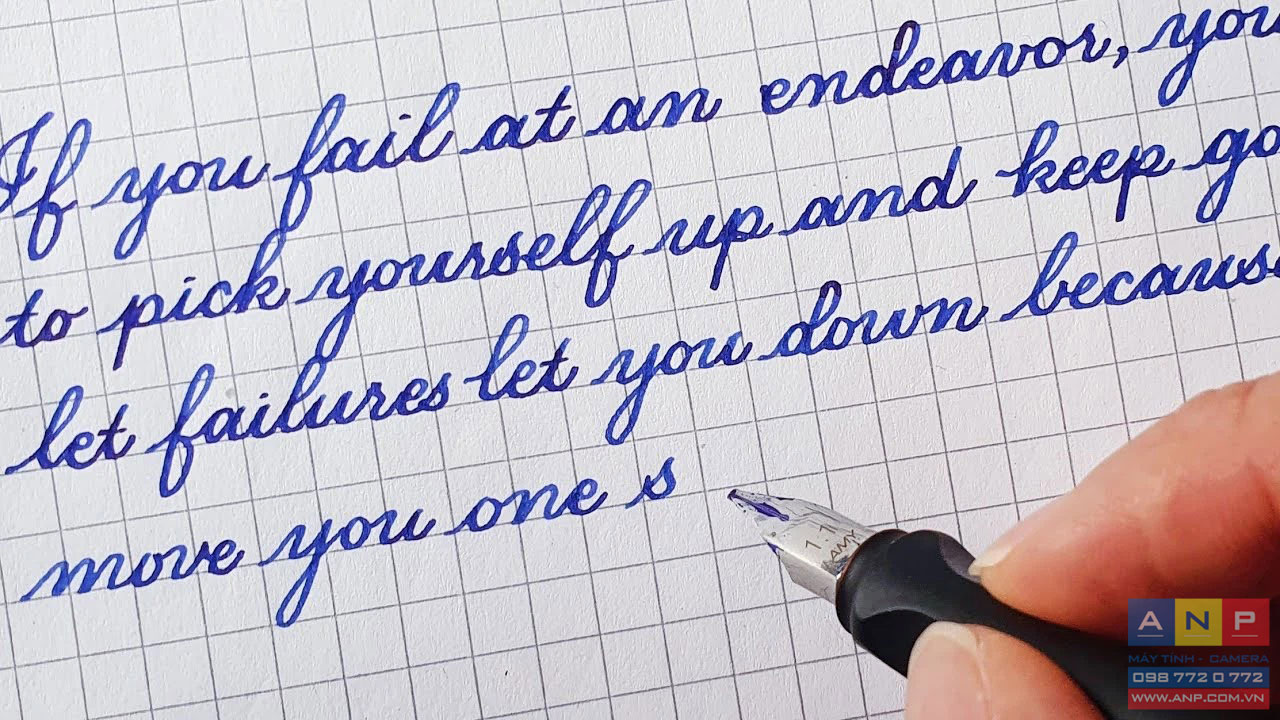
Font chữ viết tay là một loại font chữ được thiết kế để tái hiện nét đẹp và phong cách của các loại chữ viết tay từ thời kỳ cổ điển, thường là từ thập niên 1920 đến 1970. Những font chữ này thường mang đậm tính chất cổ điển, với đường nét cong, phá cách và độc đáo.
Font chữ viết tay thường có các đặc điểm như đường viền dày, các chi tiết hình học, sự kết hợp giữa chữ in hoa và chữ thường, các yếu tố trang trí như hoa văn, bóng đổ và viền. Những yếu tố này tạo ra vẻ đẹp cổ điển và sang trọng, mang lại cảm giác hoài niệm. Các font chữ viết tay thường được sử dụng trong nhiều lĩnh vực thiết kế, bao gồm in ấn, quảng cáo, thiết kế logo, bìa sách, poster và các dự án sáng tạo khác. Chúng giúp tạo ra một phong cách đặc trưng, gợi nhắc đến quá khứ và tạo điểm nhấn độc đáo cho thiết kế của bạn.
Những tính năng ưu việt của font chữ viết tay
Font chữ viết tay có một sức hút đặc biệt và mang đến nhiều tính năng ưu việt, có thể kể đến như sau:
Cảm giác cá nhân: Font chữ viết tay mang đến một cảm giác cá nhân và riêng biệt. Chúng có thể tạo ra sự gần gũi, thân thiện và tạo sự kết nối giữa người viết và người đọc. Điều này có thể làm tăng tính tương tác và sự gắn kết với nội dung được viết.
Sự độc đáo và tinh tế: Mỗi nguồn chữ viết tay đều mang trong mình sự độc nhất vô nhị và tinh tế. Các đường nét cong, các chi tiết thú vị và sự khác biệt trong từng chữ cái tạo ra một phong cách đặc trưng và thu hút.
Phong cách và cá nhân hóa: Sử dụng font chữ viết tay cho thiết kế có thể giúp bạn thể hiện phong cách riêng của mình và tạo ra sự cá nhân hóa. Bạn có thể lựa chọn các font chữ viết tay phù hợp với thẩm mỹ và tình cảm mà bạn muốn truyền tải trong dự án của mình.
Sự linh hoạt: Font chữ viết tay có thể linh hoạt và dễ dàng thích nghi với nhiều loại dự án và ngữ cảnh khác nhau. Chúng có thể được sử dụng cho thiết kế logo, poster, bìa sách, thiệp mừng, trang web và nhiều hơn nữa.
Tạo không gian lãng mạn: Font chữ viết tay có khả năng tạo ra một không gian đặc biệt, như một bản nhạc thăng hoa hoặc một cuộc hành trình ngược thời gian. Khi nhìn vào những đường cong và chi tiết của font chữ này, chúng ta có thể cảm nhận được sự lãng mạn, sự hoài cổ và cảm giác cổ điển. Điều này giúp làm nổi bật các yếu tố lịch sử và tạo ra một không gian độc đáo, đưa ta trở về quá khứ hoặc mang đến một cảm giác hoài niệm.
Top 15 font chữ viết tay vintage đẹp nên có trong bộ sưu tập
Parisienne Font
Parisienne là một font chữ viết tay vintage đẹp với nét đẹp cổ điển và sự tinh tế. Với đường nét mềm mại và nét chữ thanh lịch, Parisienne mang đến một cảm giác lãng mạn và quý phái cho các thiết kế của bạn.
Grand Estonia Font
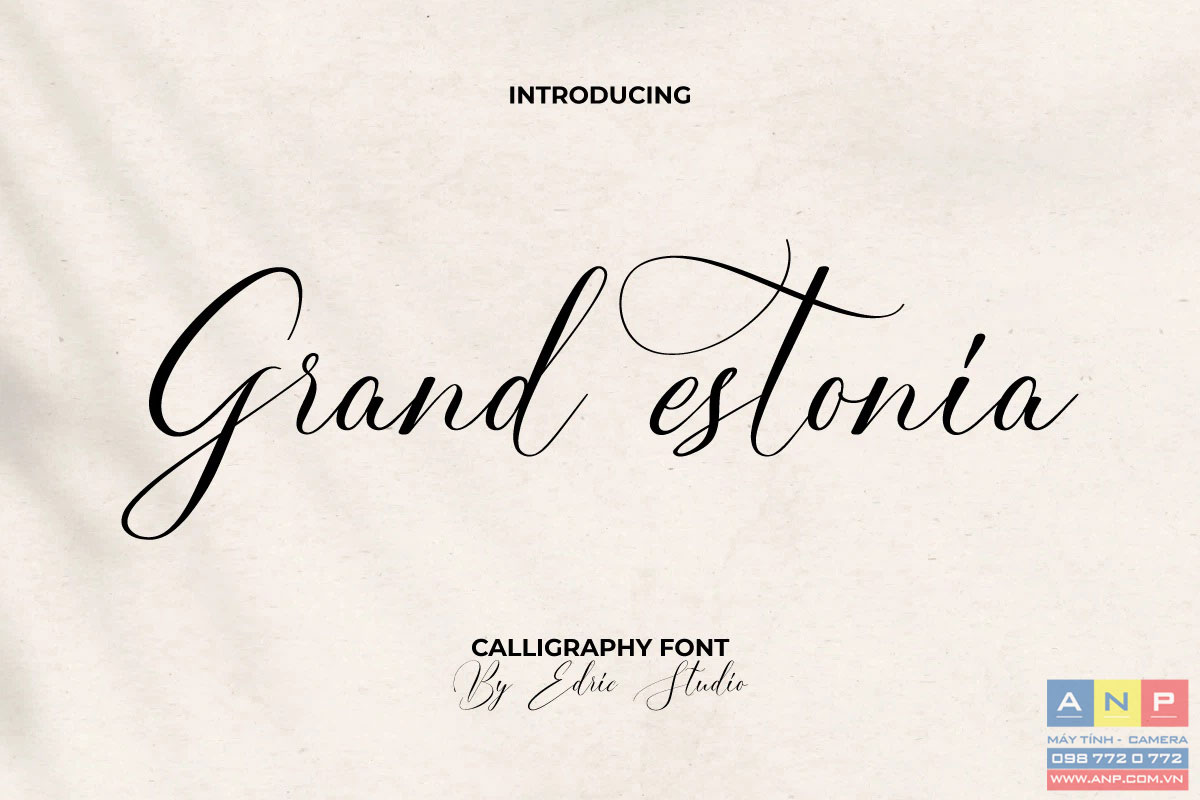
Grand Estonia Font là một font chữ viết tay vintage mang đậm phong cách Art Deco của những năm 1930. Với đường nét cong mượt mà và đường viền in đậm, Grand Estonia Font tạo ra một sự kết hợp hoàn hảo giữa sự cổ điển và hiện đại.
Sacramento Font
Sacramento là một font chữ viết tay vintage tinh tế và đơn giản. Với đường nét mềm mại và cảm giác tự nhiên, Sacramento mang đến một phong cách thân thiện và gần gũi cho bất kỳ dự án thiết kế nào.
Dancing Script Font
Dancing Script là một font chữ viết tay vintage vui nhộn và năng động. Với đường nét cong và động, Dancing Script tạo ra một cảm giác như đang nhảy múa trên giấy và mang đến một sự sôi động cho thiết kế của bạn.
Pacifico Font
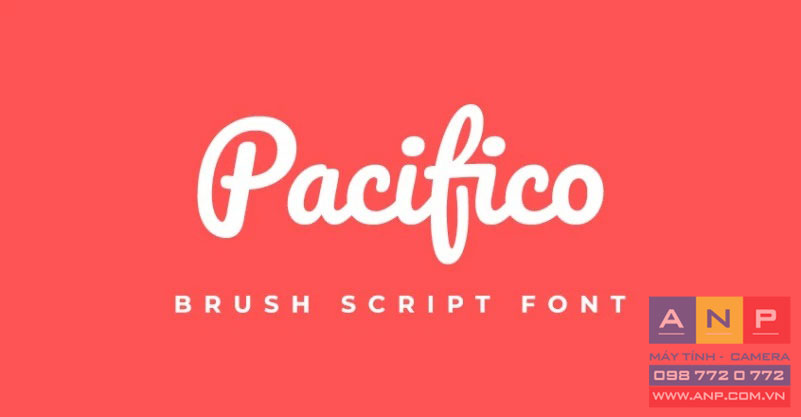
Pacifico là một font chữ viết tay vintage độc đáo và đáng yêu. Với đường viền mềm mại và những chi tiết độc đáo, Pacifico tạo ra một sự kết hợp giữa sự lãng mạn và vui tươi.
Amatic SC Font
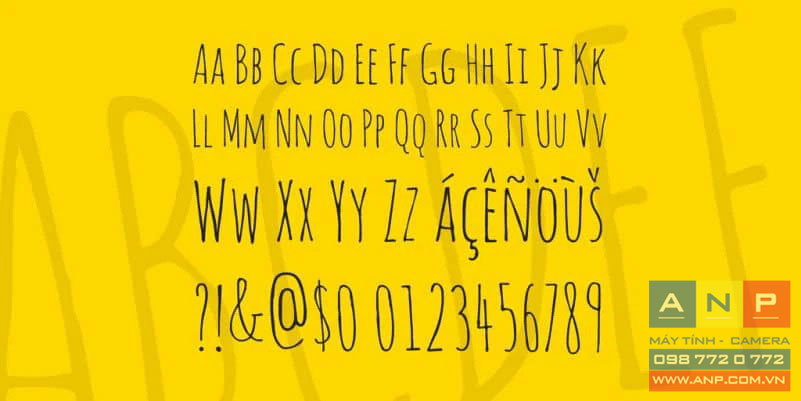
Amatic SC là một font chữ viết tay vintage đơn giản và thân thiện. Với những đường nét mềm mại và đường viền in đậm, Amatic SC tạo ra một phong cách thân quen và thích hợp cho các thiết kế đơn giản và gần gũi.
Windsong Font
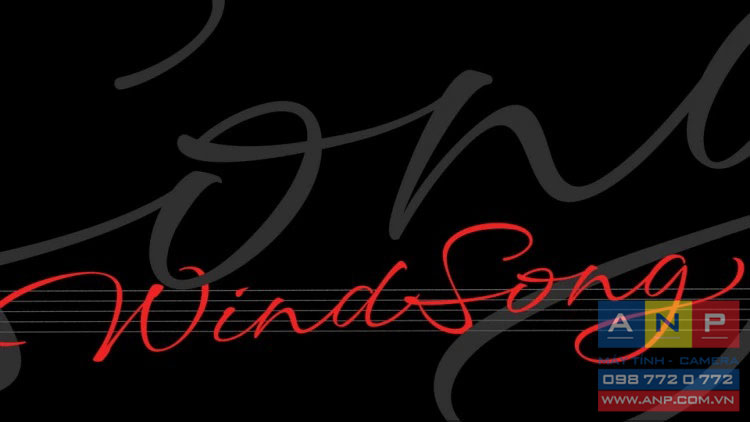
Windsong là một font chữ viết tay vintage nổi bật với đường nét cong và phong cách lãng mạn. Với sự tinh tế và cảm giác tự nhiên, Windsong mang đến một sự quyến rũ và nữ tính cho thiết kế của bạn.
Kristian Paradise Font
Kristian Paradise Font là một font chữ viết tay vintage nổi tiếng với đường viền cong và nét chữ đậm. Với sự độc đáo và cá tính của nó, Kristian Paradise Font tạo ra một phong cách đặc biệt và ấn tượng cho bất kỳ thiết kế nào.
Thomasita Font
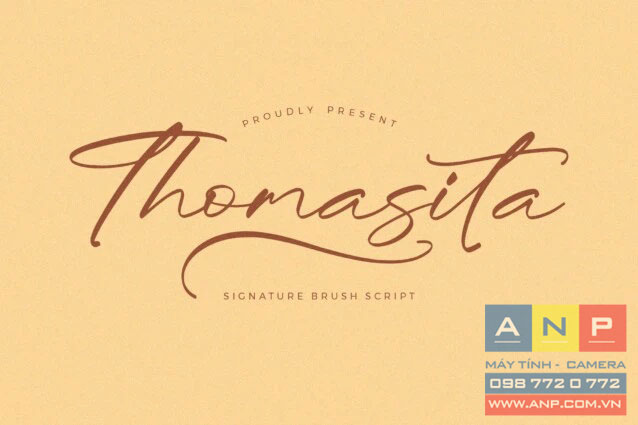
Thomasita Font là một font chữ viết tay vintage độc đáo và nổi bật. Với đường nét cong mềm mại và những chi tiết tinh tế, Thomasita Font tạo ra một phong cách cổ điển và đầy cá nhân. Sự kết hợp giữa những nét chữ in đậm và những đường viền mềm mại mang đến sự cân bằng hoàn hảo và sự thu hút cho bất kỳ thiết kế nào. Thomasita Font là một lựa chọn tuyệt vời cho việc tạo ra các dự án thiết kế vintage, retro hoặc mang tính lịch sử.
Sedoyo Rolas Font
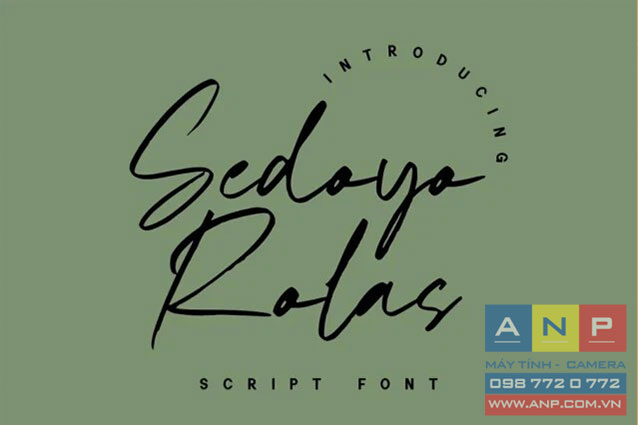
Sedoyo Rolas Font là một font chữ viết tay vintage độc đáo và sáng tạo. Với đường nét cong mềm mại và các chi tiết đặc biệt, nó mang đến một phong cách cổ điển thu hút. Sedoyo Rolas Font là lựa chọn hoàn hảo cho các thiết kế vintage, retro hoặc mang tính lịch sử và giúp tạo điểm nhấn độc đáo cho các dự án thiết kế của bạn.
Roseghale Balmoon Font
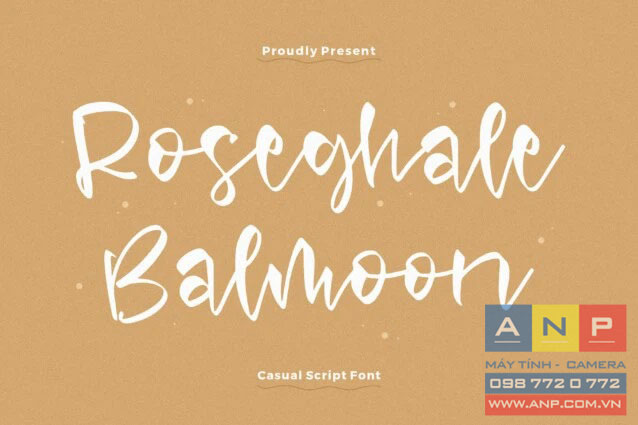
Roseghale Balmoon Font là một font chữ độc đáo và đẹp mắt. Với sự kết hợp giữa đường nét cong mềm mại và các chi tiết tinh tế, Roseghale Balmoon Font tạo ra một phong cách cá nhân và độc đáo. Nét chữ in đậm và đường viền rõ nét mang đến sự tương phản và thu hút ánh nhìn. Font chữ này thích hợp cho các dự án thiết kế đa dạng, từ thiệp chúc mừng cho đến bộ sưu tập sản phẩm thời trang.
Ramsoneth Font
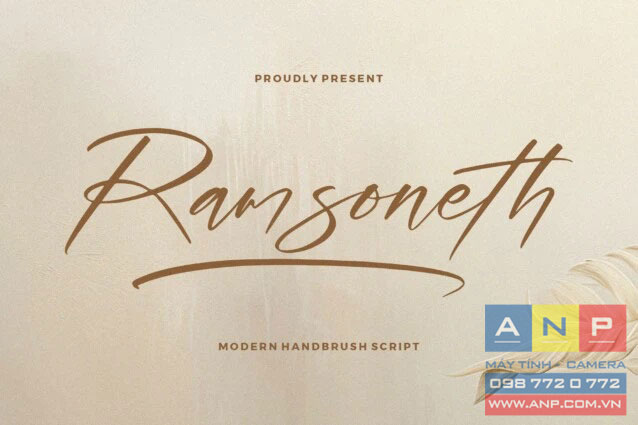
Ramsoneth Font là một kiểu chữ hiện đại viết tay, phù hợp cho mọi dự án như: logo, dự án nhận diện thương hiệu, thiết kế đồ gia dụng, bao bì sản phẩm, in lên ly, cốc, danh ngôn, poster, túi mua sắm, áo thun, bìa sách, thẻ tên, thẻ mời, thiệp chúc mừng, nhãn, nhiếp ảnh, chữ ký số, sự kiện đặc biệt và tất cả những dự án khác cần một phong cách chữ đẹp mắt.
Authentic Style Font
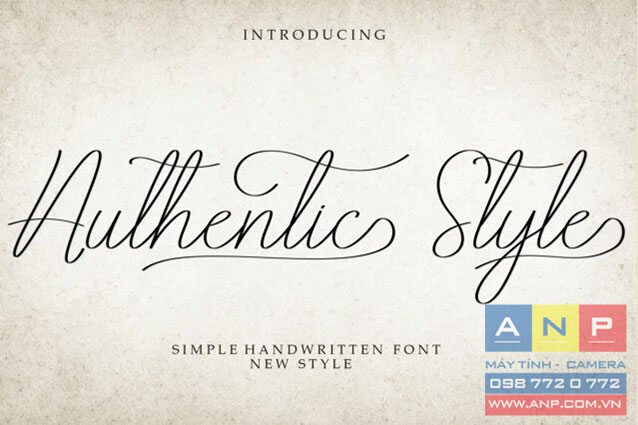
Authentic Style Font mang đến một kiểu chữ viết tay ngọt ngào và thân thiện. Kiểu chữ này lý tưởng cho việc viết thiệp cưới, thẻ chúc mừng, hoặc bất kỳ thiết kế nào cần một chút vui tươi!
Moon Merry Font
Authentic Style Font mang đến một kiểu chữ viết tay ngọt ngào và thân thiện. Kiểu chữ này lý tưởng cho việc viết thiệp cưới, thẻ chúc mừng, hoặc bất kỳ thiết kế nào cần một chút vui tươi!
Moon Merry Font
Wantsignature Font mang lại sự mạnh mẽ và nổi bật với đường nét đậm, tạo nên một cái nhìn mạnh mẽ và quyến rũ. Các chữ cái được thiết kế với độ chi tiết và tỉ mỉ, tạo ra sự cân đối và hài hòa trong từng ký tự. Điểm đặc biệt của Wantsignature Font là sự đậm nét và sự táo bạo trong cách nét chữ được thiết kế, tạo ra một phong cách tự tin và cá nhân.